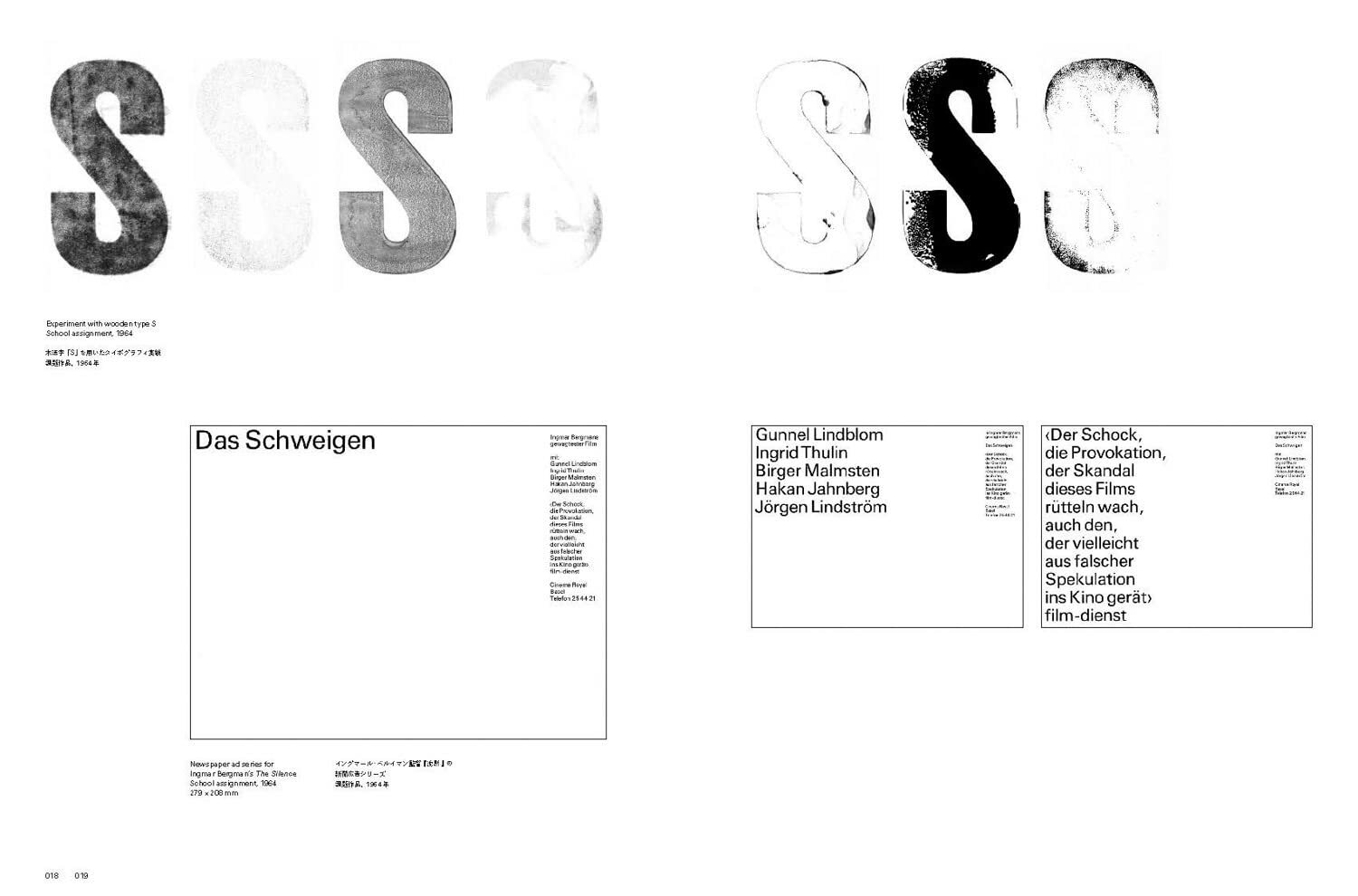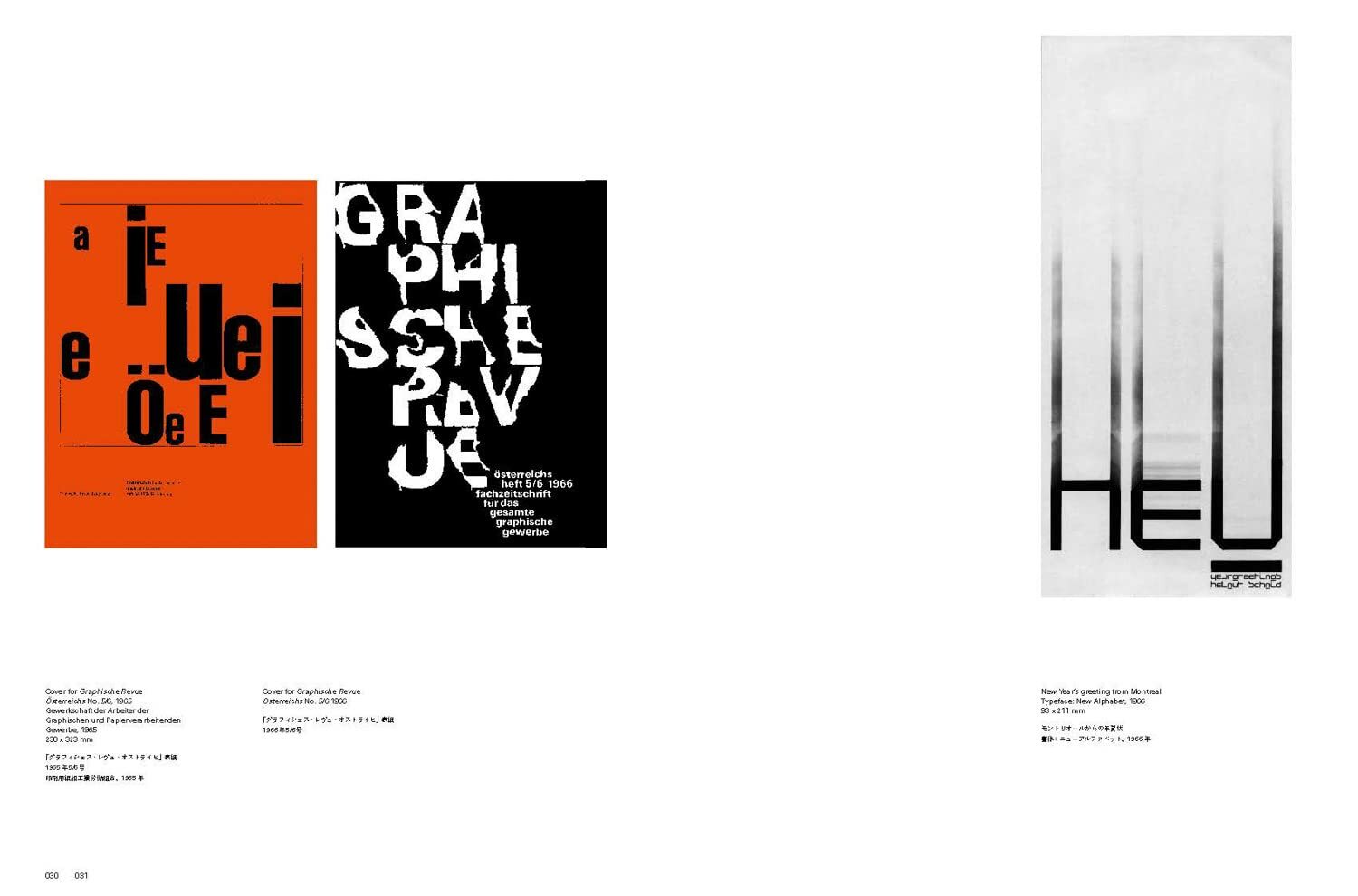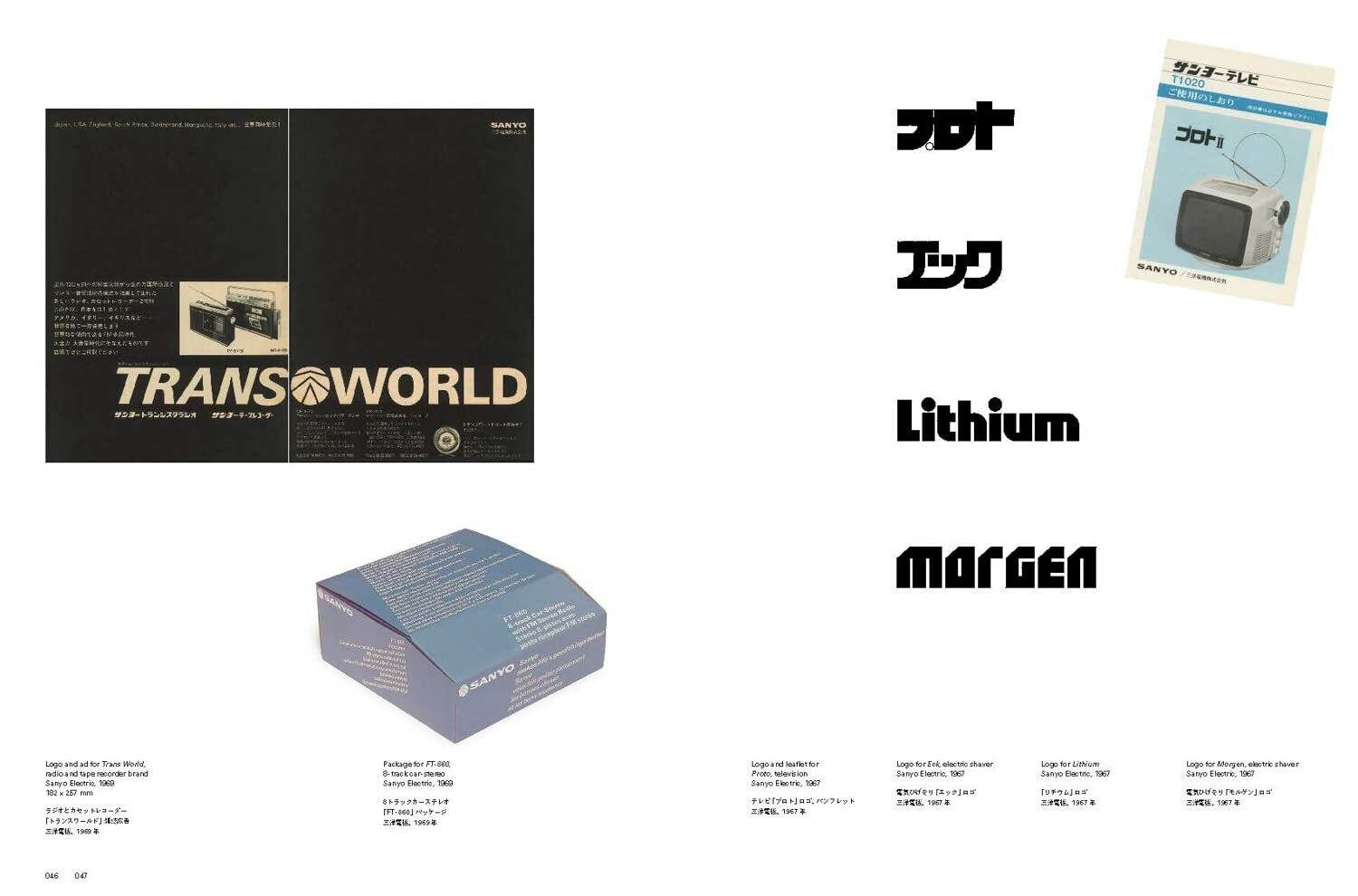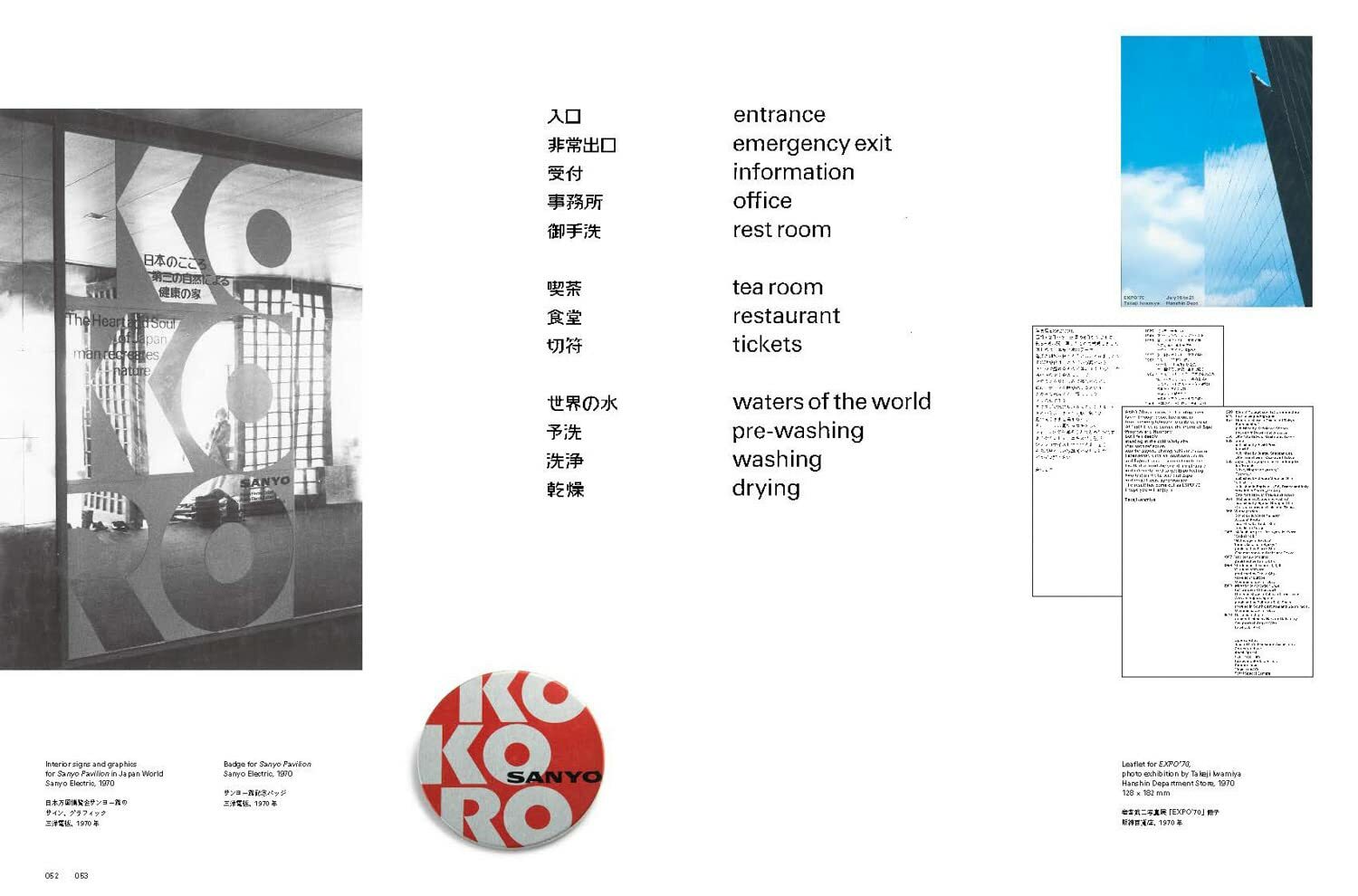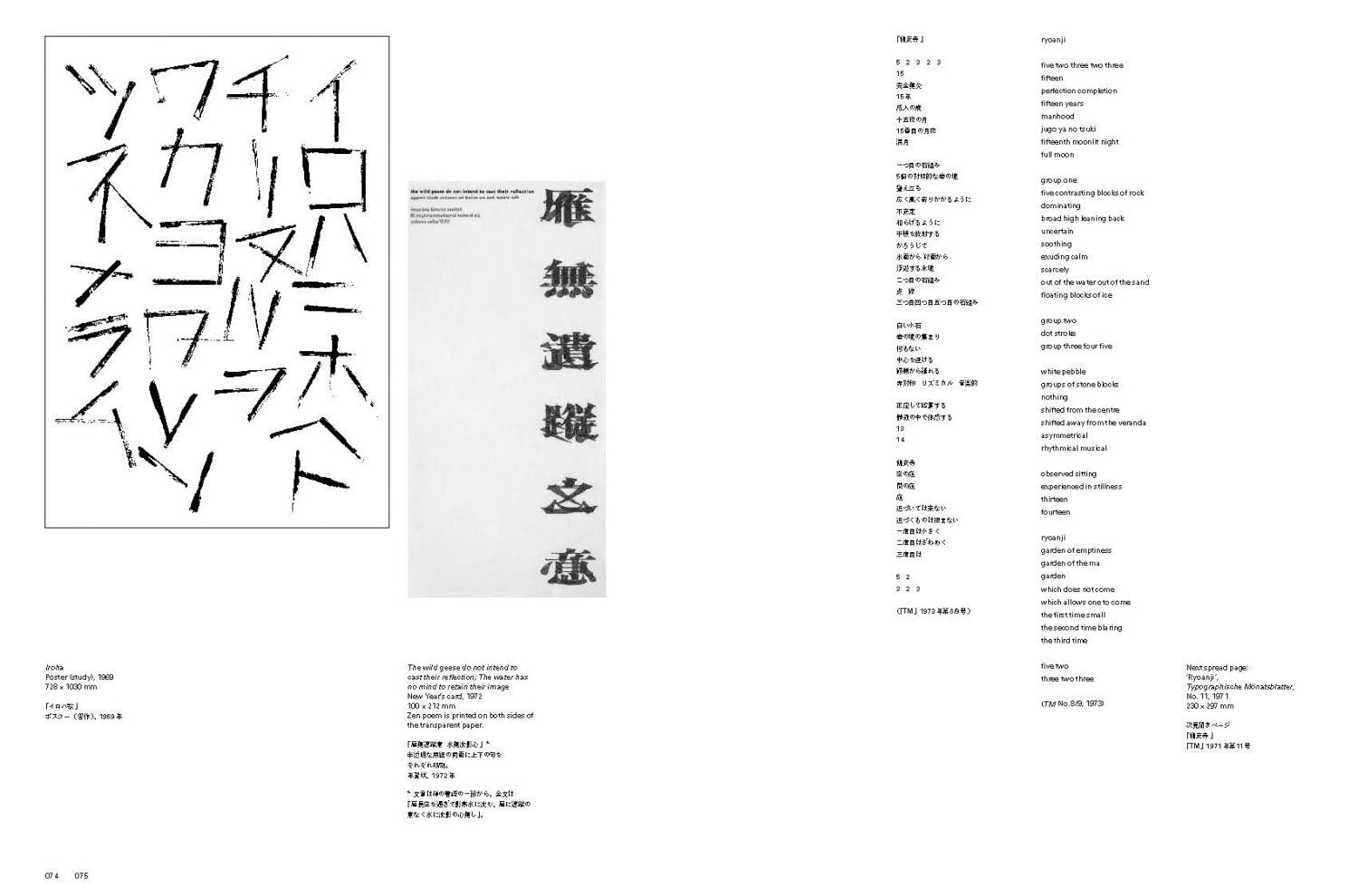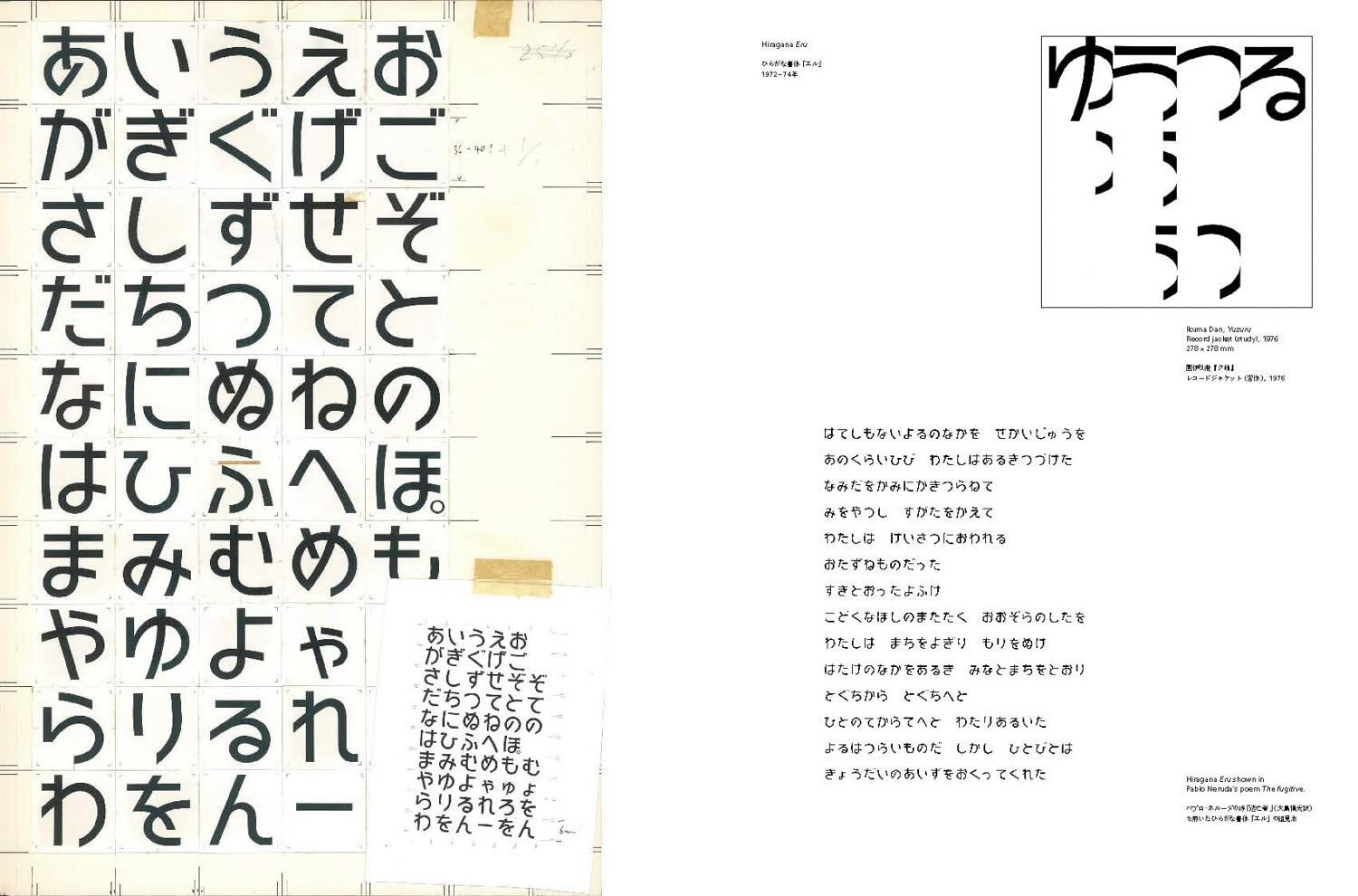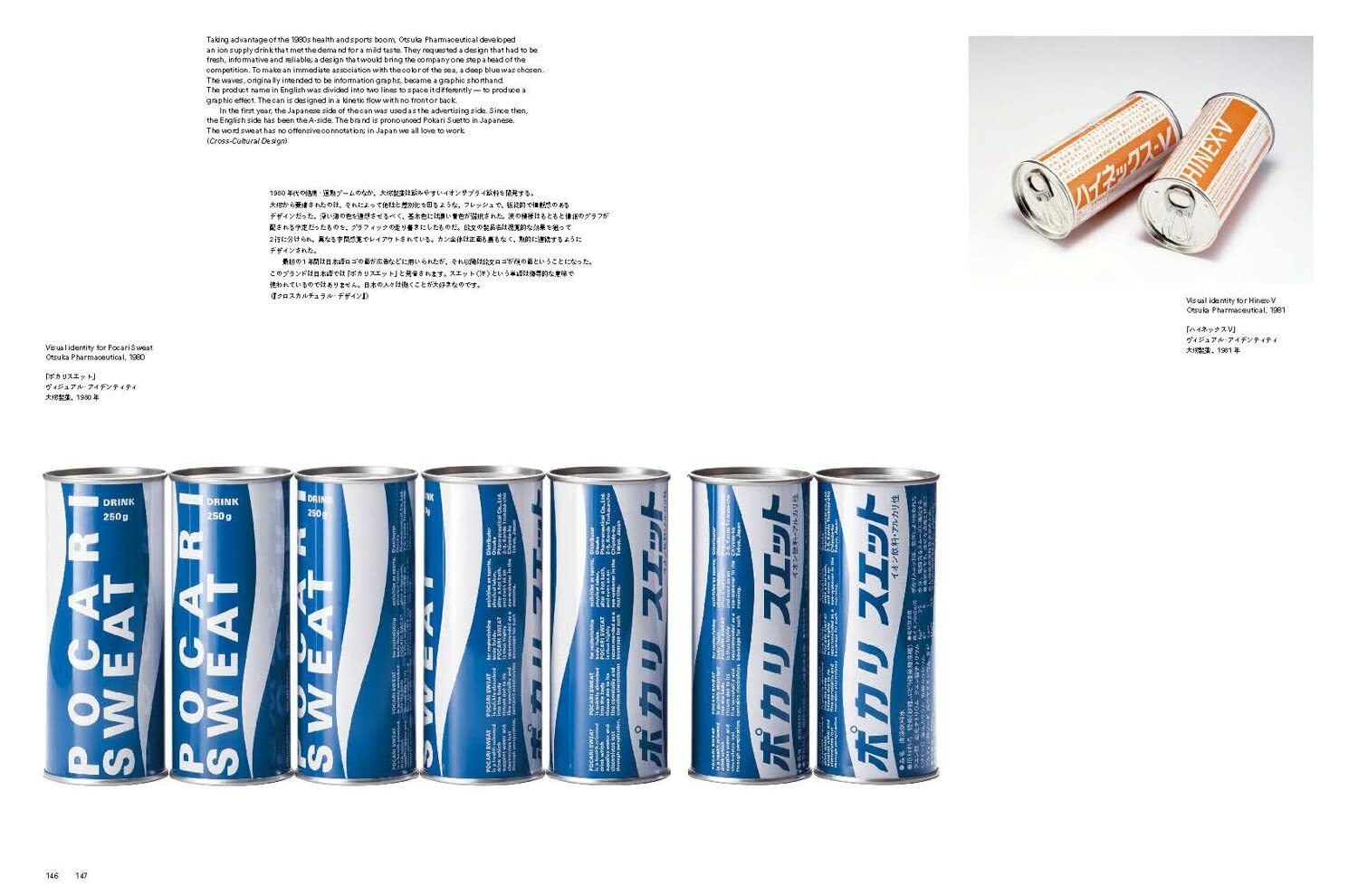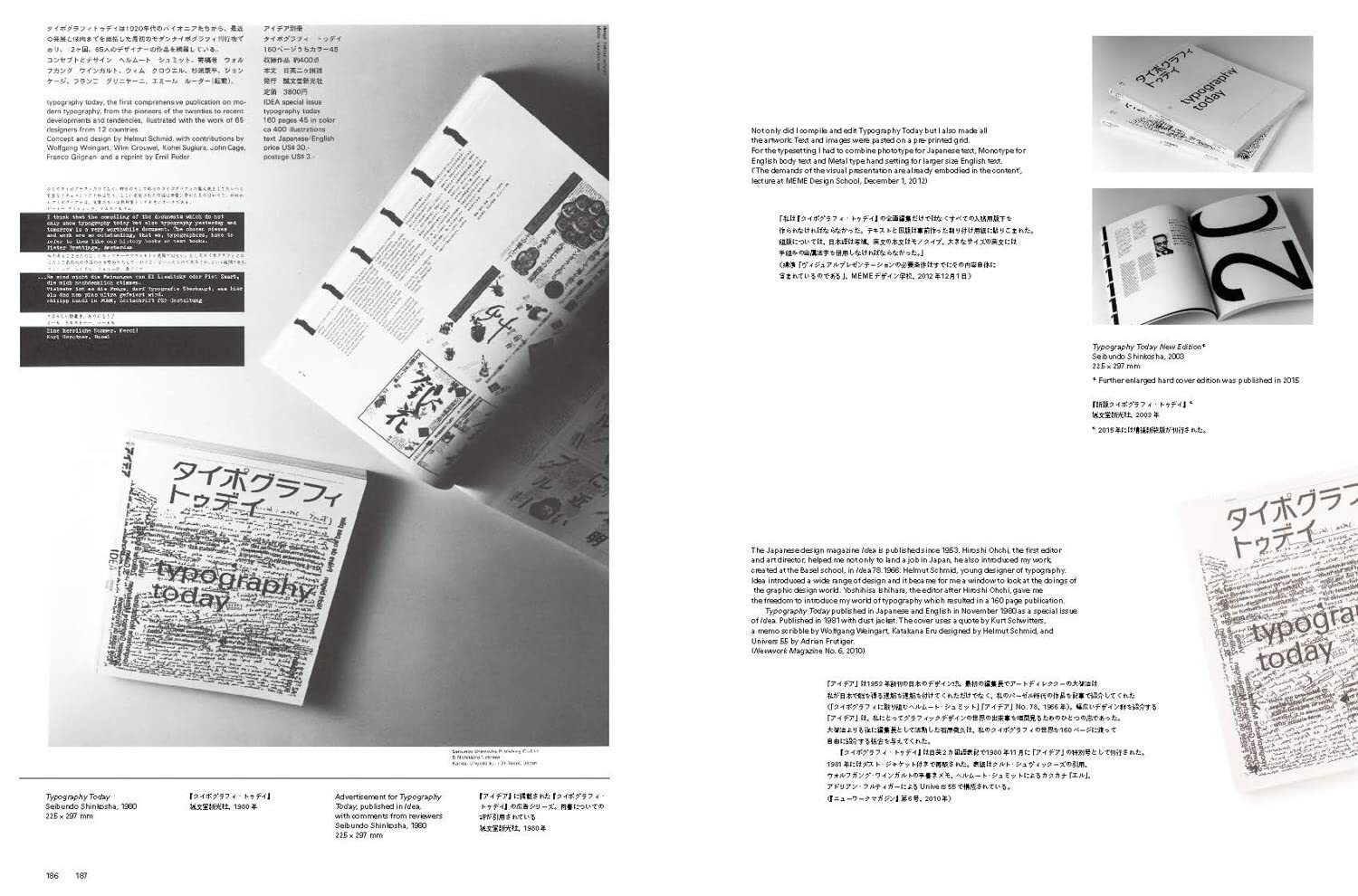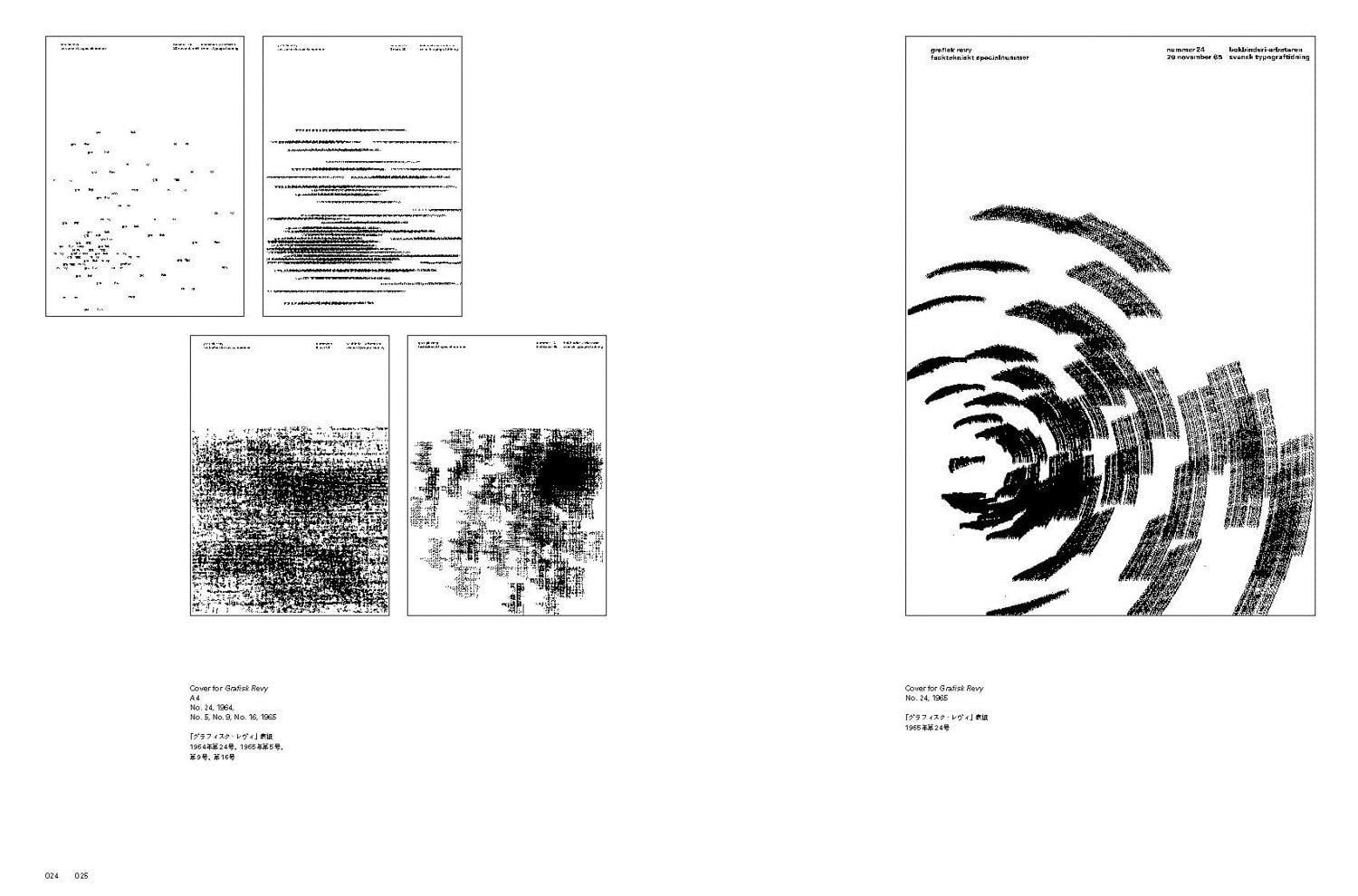
Helmut Schmid: Typography: Typography / Typografie
【書籍簡介】
奧地利字體排印與平面設計師 Helmut Schmid(1942–2018)是國際設計界公認的大師,他的作品以極致的清晰、簡潔與優雅著稱。受瑞士設計師 Emil Ruder 的影響,Schmid 在忠於其設計原則的同時,也發展出獨特的風格。他的設計生涯橫跨歐洲與亞洲,曾旅居大阪、溫哥華與德國,並在德國社會民主黨工作,為總理 Willy Brandt 和 Helmut Schmidt 進行設計專案。這些經歷使他能夠融合東西方的設計美學,並在編輯設計、產品包裝、政治與企業識別等領域留下深遠影響。
《Schmid Typography》這本雙語專書全面回顧了他的設計生涯與作品,透過精心編排的版面,讓每張圖像得以自在呈現,而附帶的文字則以流暢且富有敘事感的方式,記錄了他的生平與職業歷程。本書不僅展現了 Schmid 在字體排印領域的卓越成就,也與《Weingart: Typography》及《Ruder Typography, Ruder Philosophy》相輔相成,完整構築了 Lars Müller 出版社對巴塞爾字體學派的研究脈絡,為這一學派的發展補上關鍵的一塊拼圖。